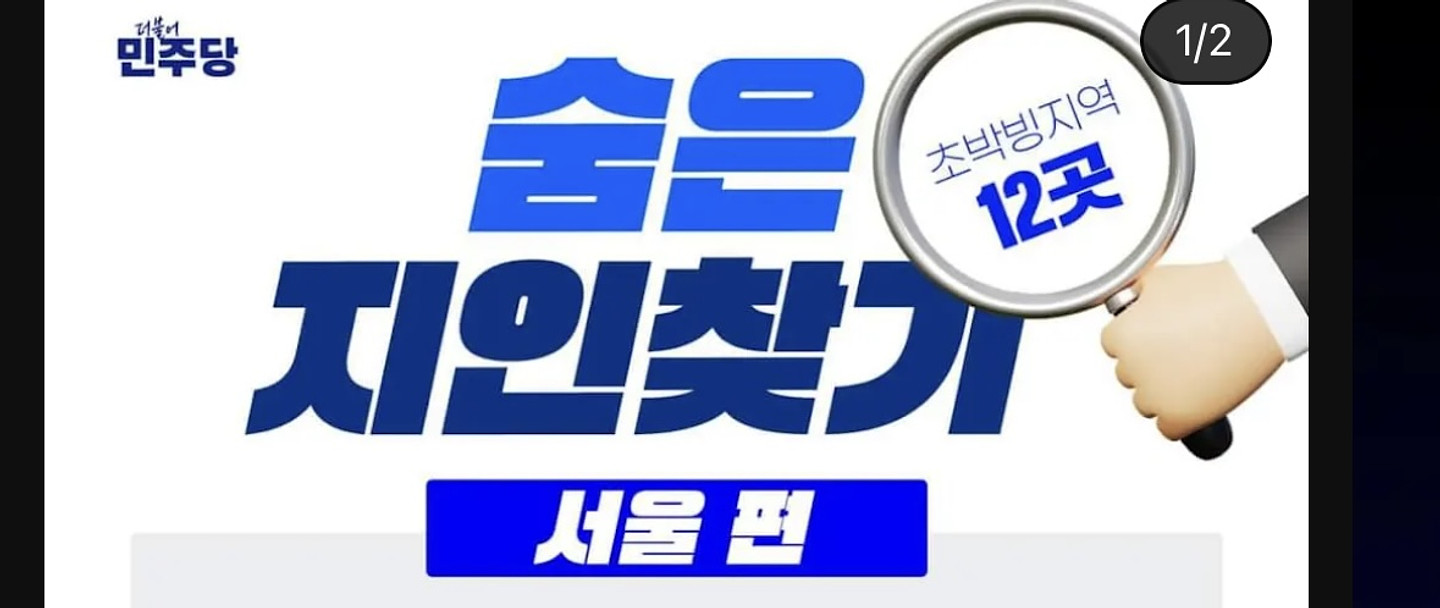
이 폰트가 궁금해요? 아시는 분 답변 부탁드려요. 그리고 글자 기울기는 원래 그런건지 아니면 이미지로 변경하는건지도 궁금해요
210 수퍼사이즈
기울기 효과가 적용되어 있는 폰트입니다 https://www.design210.com/cloud/item.detail.renew?idx=228